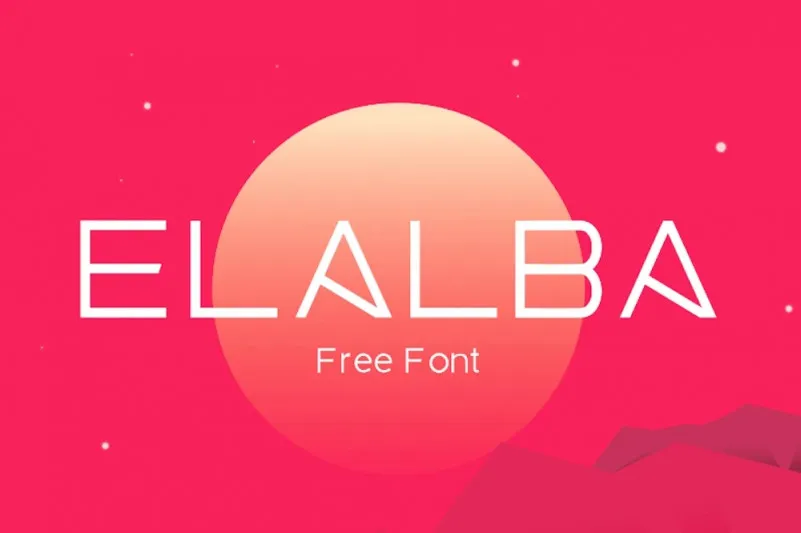
Elalba Font – Fonte Grátis
Elalba Font
A ‘Elalba Font’ é uma opção versátil para projetos que exigem tanto seriedade quanto criatividade. Ela foi meticulosamente criada pela designer 99designs, seguindo os moldes de um tipo de serif livre. Com seu conjunto completo de caracteres incluindo letras maiúsculas e minúsculas, números, pontuação e muitos caracteres multilíngues, a ‘Elalba Font’ se destaca como uma fonte sutil que é perfeitamente adaptável para uso em grandes diapositivas, títulos de apresentação, postais, marketing e propaganda. Com essa fonte em sua caixa de ferramentas, você pode criar designs profissionais e criativos sem hesitar.